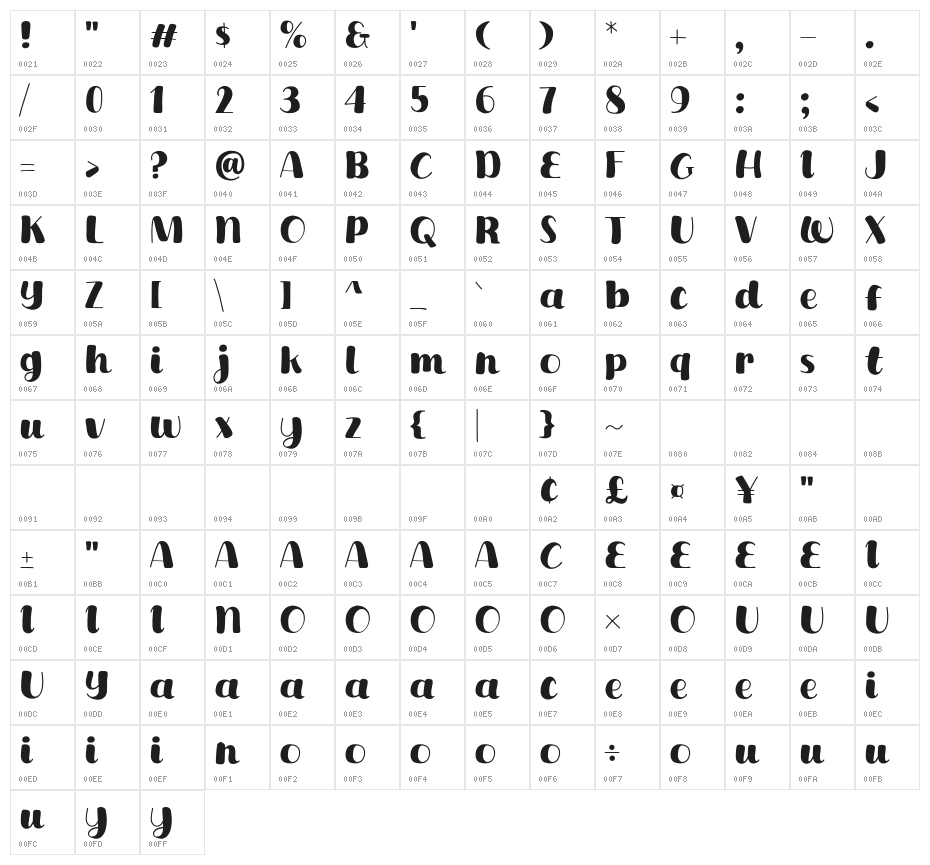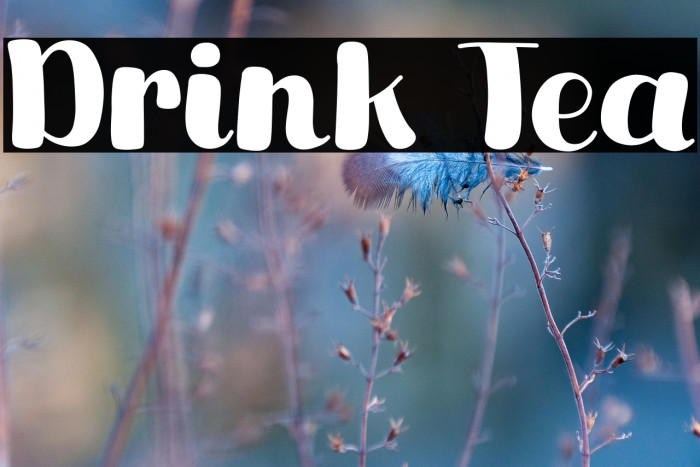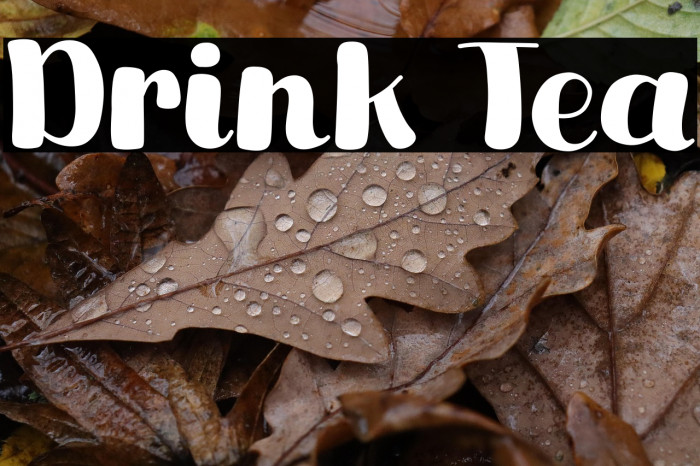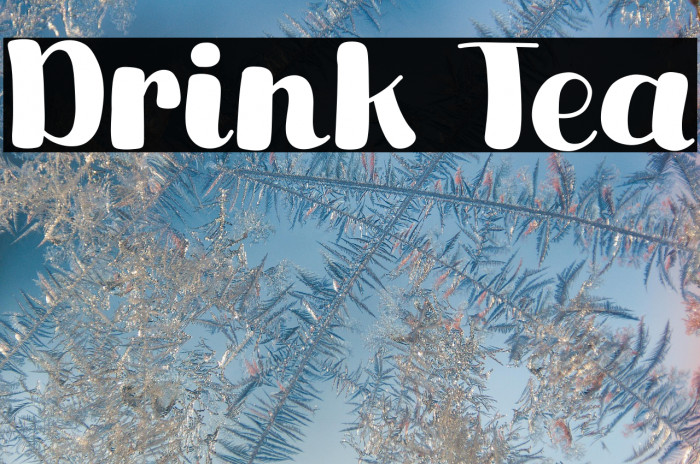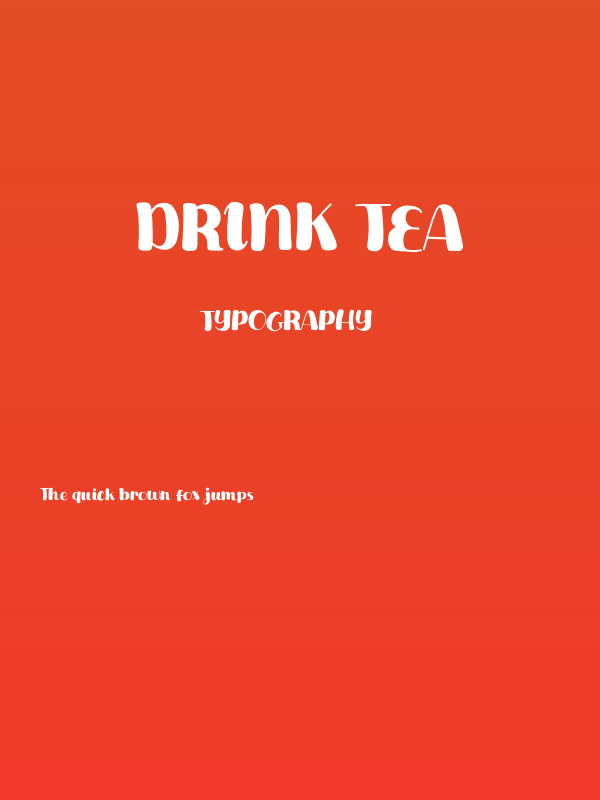
Drink Tea Font
| Stile generale | Playful, Whimsical |
| Progetti proposti | Ideal for children's books, playful branding, posters, and creative invitations. |